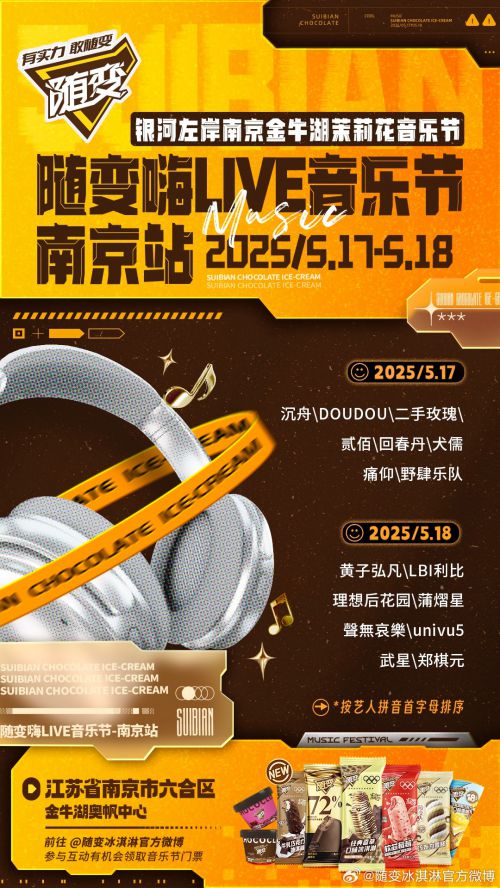
点字机械体架结构采用更加能体现机械感的正方形为框架进行设计,竖划的起笔凸起处理以及收笔的切角处理外加的撇捺的出笔,共同构成字形的鲜明个性.运用线性镂空来增强字体的立体感,以体现机械感与未来感。点字机械体笔画厚重,棱角分明,粗壮稳健,富有庄重感,字形结体严谨,点画硬朗。适用于标题,个性品牌推广以及广告游戏等等。
杨依磊
探寻文字风景路上的字体设计师